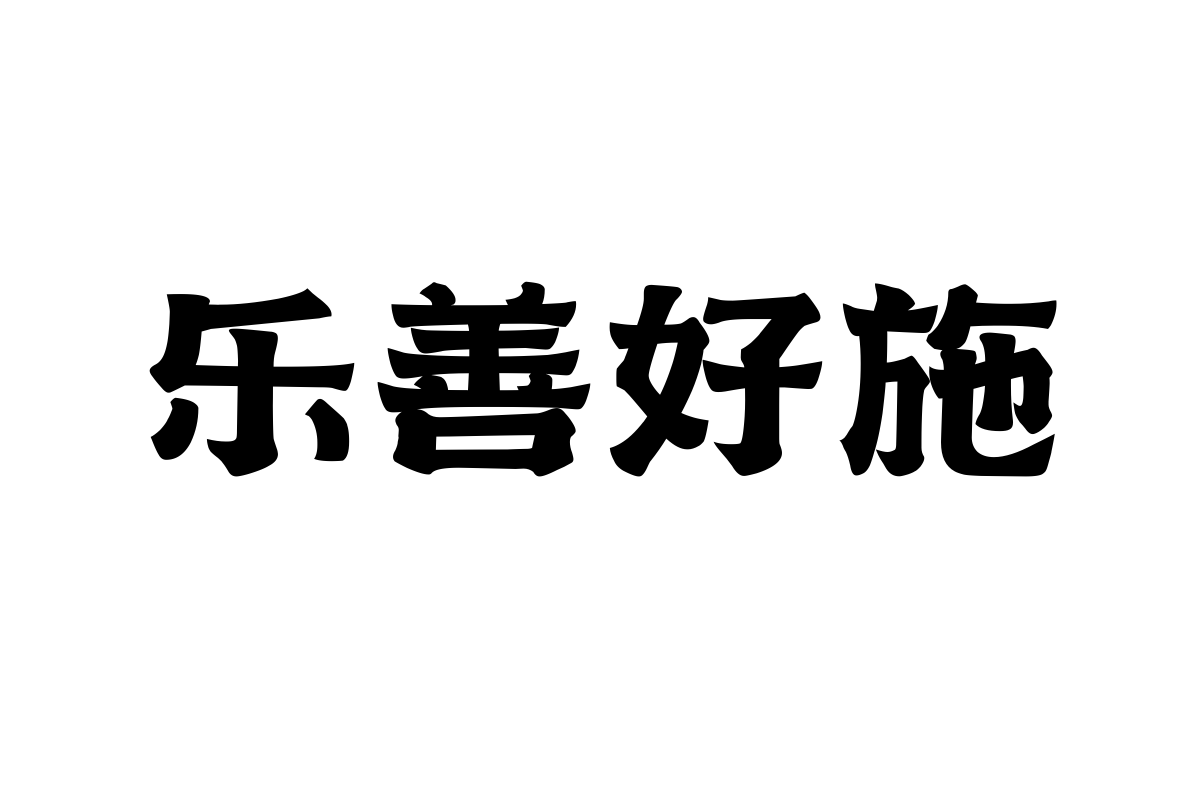
上首醒狮体是一款具有中国传统特色的书法字体。它源自中国书法艺术的精髓,以简洁、流畅、有力的笔触展现出独特的美感。上首醒狮体的字体特点包括:
1. 结构紧凑:上首醒狮体的字形结构紧凑,笔画粗细适中,线条流畅,给人以强烈的视觉冲击力。
2. 笔势刚劲:上首醒狮体的笔势刚劲有力,表现出一种坚韧不拔的精神风貌。
3. 韵味十足:上首醒狮体的韵味十足,既有古典之美,又有现代气息,适合用于各种场合的书写和设计。
4. 易于识别:上首醒狮体的字形独特,易于识别,有利于提高作品的艺术价值。
5. 适用范围广:上首醒狮体适用于各种文字设计,如标题、正文、广告、商标等,具有较强的实用性。
总之,上首醒狮体是一款具有浓厚中国传统文化特色的书法字体,其独特的风格和韵味使其在各类设计作品中备受青睐。